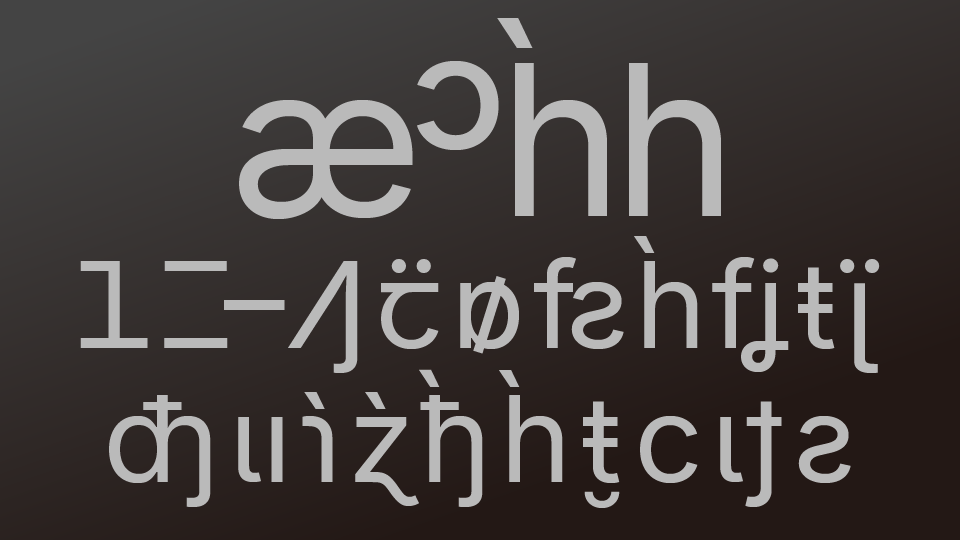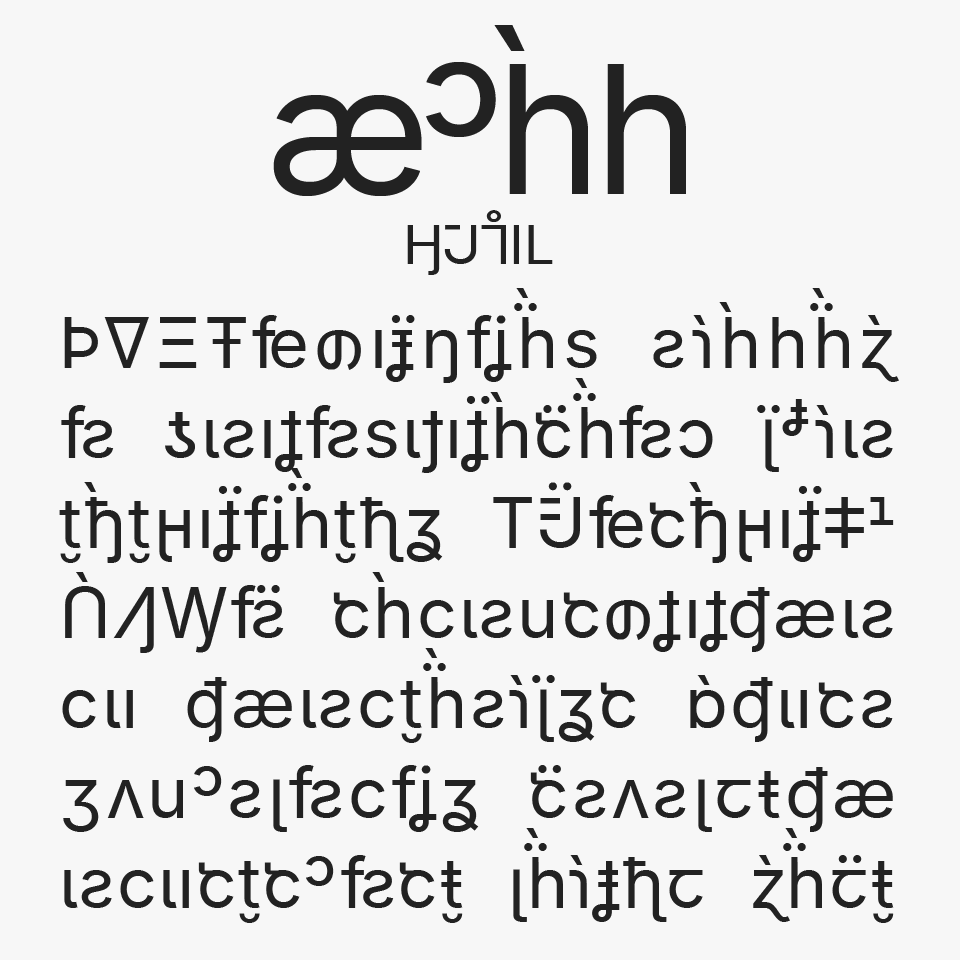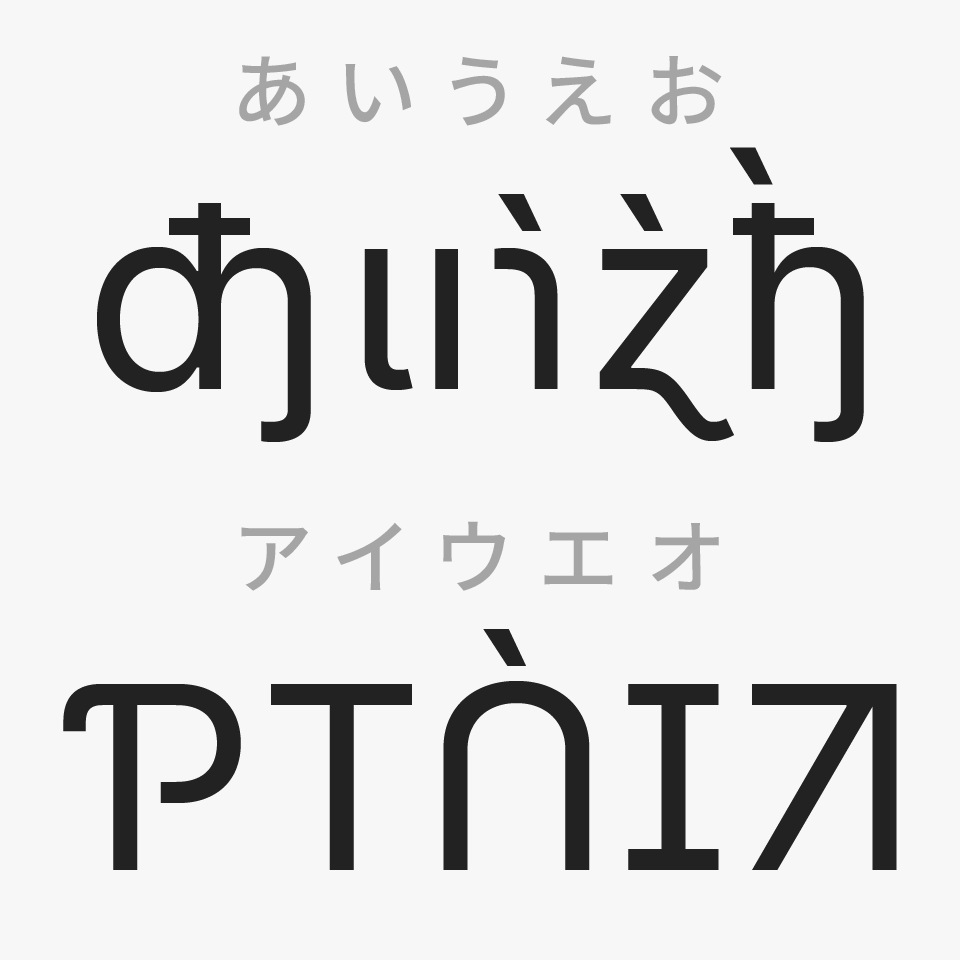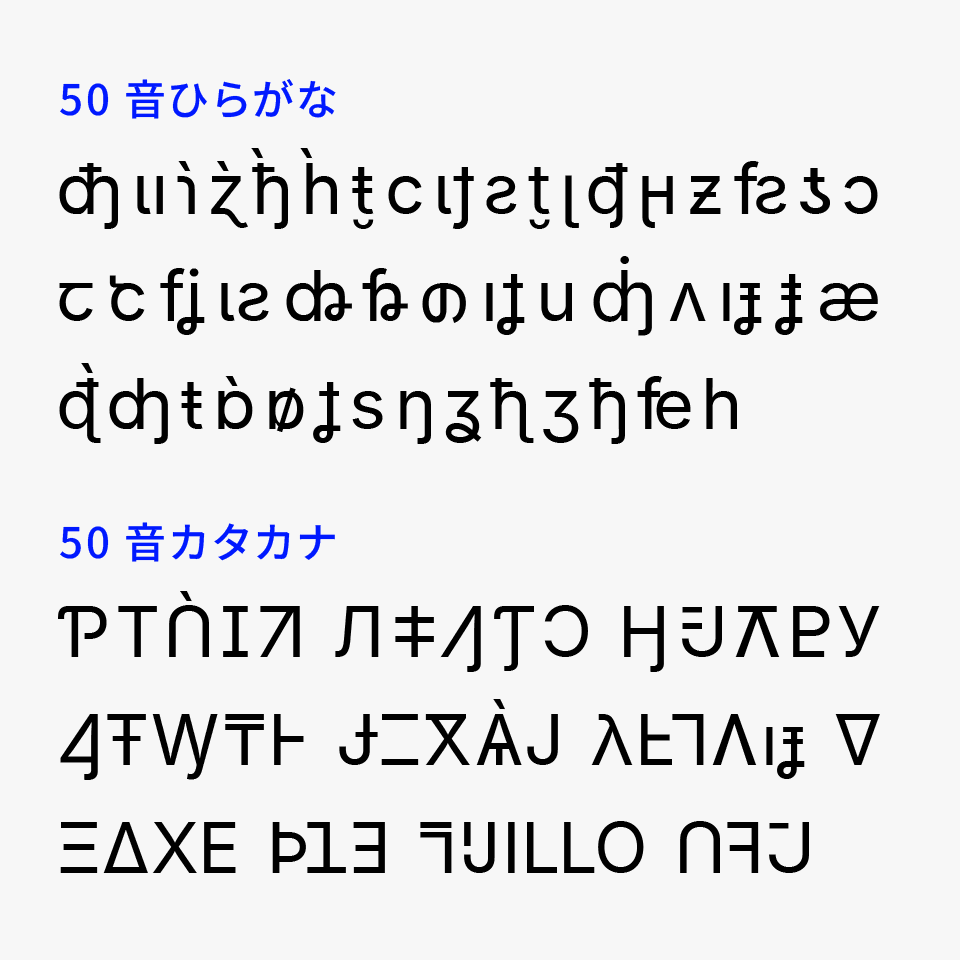
みっかん
みっかんフォントは、記号やアルファベットを組み合わせて日本語のかな文字のように見せているユニークなデザインフォントです。
一般的な読ませる文字というよりも視覚的な面白さやインパクトを重視しており、独特な記号性や異質感によって強い個性があるフォントです。日本人にだけ読めないフォント(Electroharmonix)ならぬ、日本人にしか読めないフォントのような雰囲気あるフォントです。
パッと見ではなかなか読めないようにも感じますが、規則性が見えてくると日本語に見えてくるようになります。
異世界の文字や記号や暗号にようにも見えるので、クイズや謎解き系にも活躍できそうです。また既存のデザインにはない独自性を演出しやすく、アート作品や音楽ジャケット、ファッションビジュアル、コンセプトサイトなどにぴったりなフォントです。